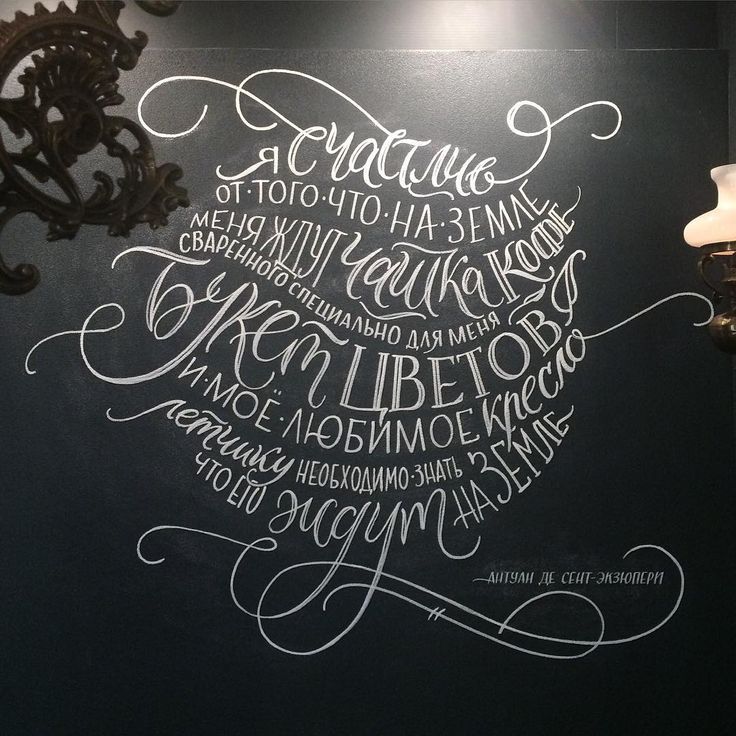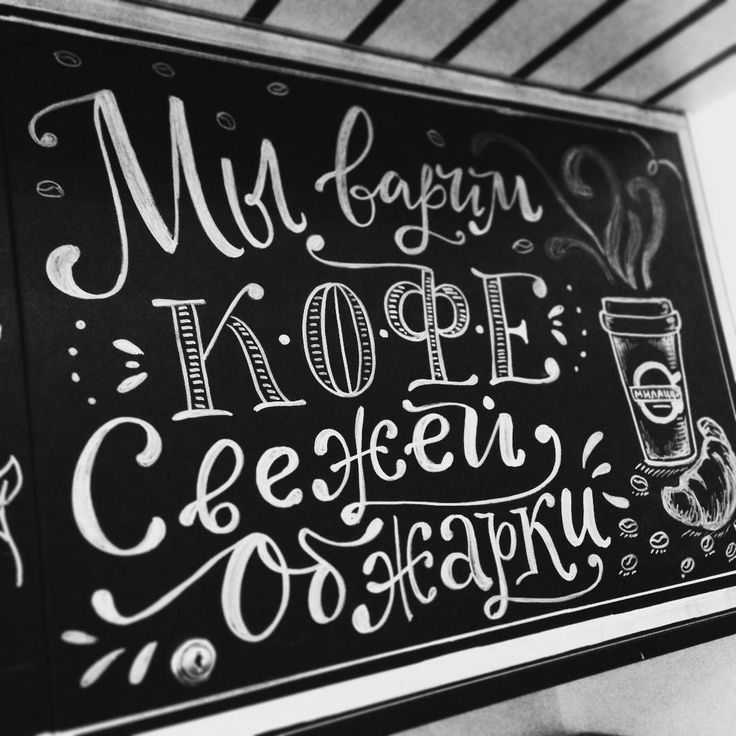
Меловой русский шрифт: ТОП русских шрифтов мелом для Photoshop и web
Художник шрифта Юрий Гордон о Лабиринте кириллицы — pop-up памятнике русской письменности перед Манежем
Перед западным фасадом «Манежа» появился настоящий памятник кириллице — в pop-up формате: лабиринт в форме буквы «а» рассказывает об истории кириллической письменности от средневековья до современности. Кроме того по всему городу появились «памятники буквам» от Покраса Лампаса, Шишкина-Хокусая и других художников. «Собака.ru» поговорила с автором лабиринта — одним из самых известных российских художников-типографов Юрием Гордоном (создал шрифты для половины российского глянца!) о том, как введенный Петром I шрифт «породил» Пушкина и Достоевского и о реализованном проекте памятника Бродскому.
Юрий Гордон
Ваш проект — про шрифтовую культуру?
Этот проект не связан сильно именно со шрифтовой культурой, может, чуть больше с типографической. Этот проект, придуманный Андреем Пуниным (прим.
ред. художник, архитектор, куратор художественных проектов, руководитель студии ARKI—кинетическая архитектура
«Надо понимать, что кириллица — это не наше национальное достояние, а это письменность, которую используют в Украине, Беларуси, Сербии, Черногории, Болгарии, я уже не говорю о Монголии».
Кириллицы становится все меньше и меньше, в той же Сербии.
Да, ареал ее распространения с падением социалистического лагеря стал уже. Но это не значит, что она стала хуже.
Что такое «вкус текста»?
Это когда шрифт воздействует на читателя определённым образом.
То есть, если вы наберёте один и тот же текст разными шрифтами и прочтёте его, вы увидите, насколько по-разному он на вас действует.
Вроде, это очевидная мысль?
Очевидная мысль, но классическому типографу кажется, что шрифт должен быть нейтральным, чтобы потеряться при чтении. Но на самом деле, это не так. Книга может стать весёлой или грустной в зависимости от того, каким шрифтом она набрана. Она может оставить тоскливое впечатление или порадовать. Послевкусие от чтения очень сильное, и я это проверял на себе экспериментально, скажем, я читал Пруста, набранного 4-мя разными шрифтами.
Что произошло с восприятием шрифтов с наступлением цифровизации?
С тех пор, как читаю только с айфона, я перешёл на другие шрифты, потому что понял — в короткой экранной строке шрифт действует совершенно иначе, чем в книге. То, что мне нравилось в книге, начинает меня раздражать ужасно на айфоне. Это другой тип чтения, так что это важно.
Текст, набранный шрифтом Times new roman — возможно, самым популярным в России в 90–2000-е годы
Шрифт San Francisco на экране iPhone 11
В 90-е появилась операционная система Windows и редактор Word со шрифтами по умолчанию, для многих именно шрифт times new roman стал олицетворением того, как выглядит кириллический шрифт.
А как называется дефолтный шрифт сегодняшнего дня?
Для меня сейчас дефолтный шрифт – Сан-Франциско, шрифт который используется в iPhone.
Мне кажется, изменение письменности и вида кириллицы — неочевидные процессы для людей, которые не связаны с дизайном. Какое послание широкой аудитории вы несете своим Лабиринтом?
Лабиринт рассказывает историю кириллицы по-новому. Мне кажется, что я выделяю те вещи, которые мало кем осмыслены, например, влияние шрифта на рост культуры. Или то, как частное предпринимательство и негосударственные инициативы ведут к культурному взлёту через такие вещи, как типографика.
Почему экспозицию о кириллице вы «закрутили» в лабиринт?
Это важно: лабиринт — место, где можно запутаться, и место, где невозможно одновременно получить всё сразу. Для того чтобы его понять, надо пройти 3 маршрута. Самый короткий маршрут называется «Глаголица», и он состоит буквально из одного маленького зала, в который входишь и выходишь — маршрут «обманка», как и сама глаголица: она началась и кончилась.
Второй маршрут очень длинный, идет вдоль всей стены лабиринта и называется «Петровский». Это рассказ о том, как развивалась кириллица до петровской реформы и после неё. Там я почти не говорю о рукописной традиции, потому — она вынесена отдельно, но много говорю о петровской культуре в целом, о том, что важно в реформе Петра, а именно о секуляризации.
«Сделать выставку про кириллицу в виде лабиринта важно: лабиринт — место, где можно запутаться, и место, где невозможно одновременно получить всё сразу».
Главное, что сделал Пётр – в 1708 году он отделил книгу от церкви, для печати светских изданий он ввел новый Гражданский шрифт. Этим шрифтом набирали гражданские книги, всё, что не священное — это и есть старт современной великой русской культуры. Этот современный шрифт привел к появлению Пушкина, Толстого и Достоевского. В момент петровской реформы произошло и трагическое для письменности событие, потому что раньше типографские наборные литеры соответствовали тому, что писали руками, как сейчас в латинице.
Скоропись читать очень сложно современному человеку, сейчас это смогут сделать только историки.
Зато она очень хорошо выражала национальные черты своей размашистостью, избытком элементов, невыработанными формами письма и так далее. Скорописи как раз и посвящен 3-ий маршрут нашего лабиринта, который показывает, как развивалось русское письмо вне петровской реформы. Там видно, как писал чиновник в середине XVIII века, насколько это непохоже на современное наше письмо, как писал Пётр I, как писал писарь Меньшикова. Там же зритель увидит, как писал запорожец в договоре Богдана Хмельницкого с царем Алексеем Михайловичем — это удивительная скоропись, непохожая на «московскую», зато похожая на европейский слитный курсив.